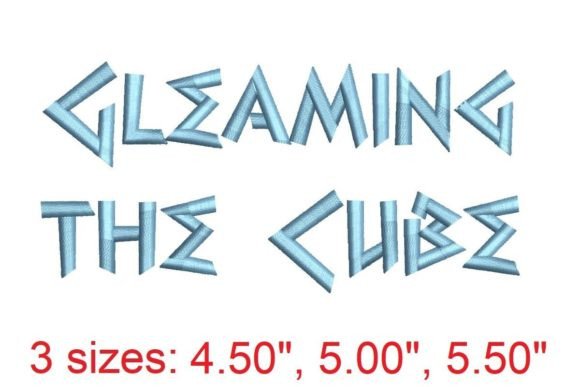
Gleaming the Cube Embroidery Font
Jika anda sedang mencari aset berkualiti tinggi seperti Gleaming the Cube Embroidery Font, pakej premium ini merupakan pilihan yang hebat untuk projek kreatif anda.